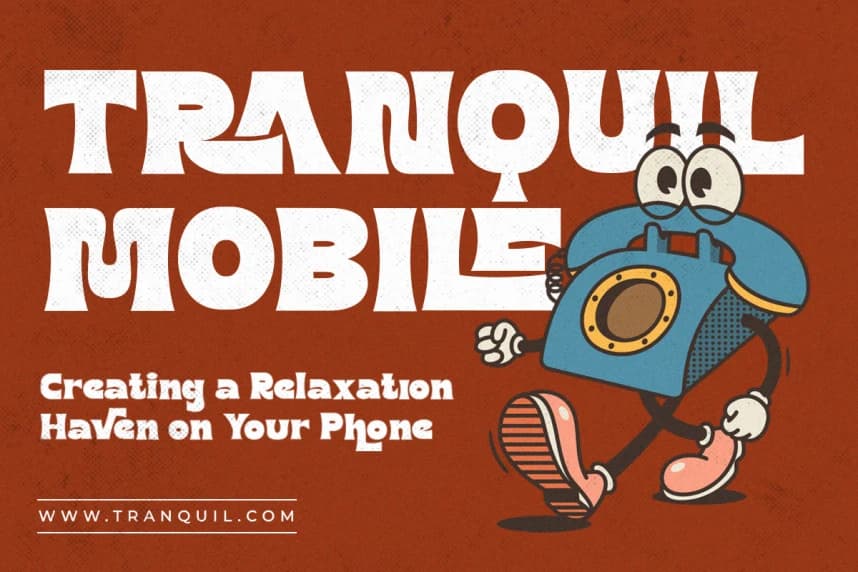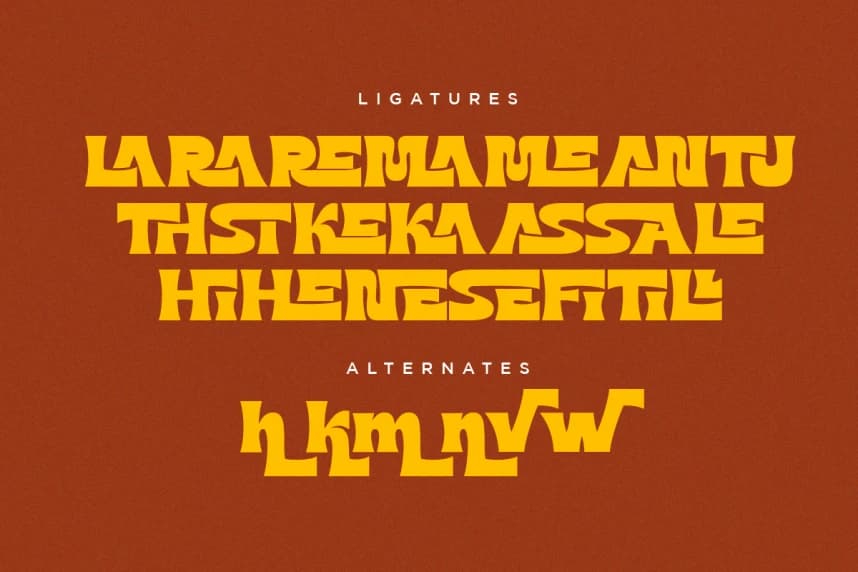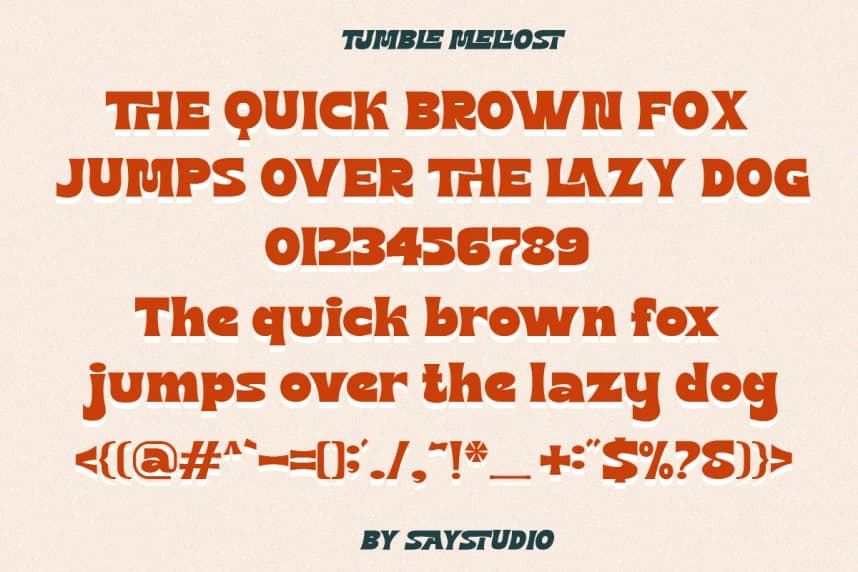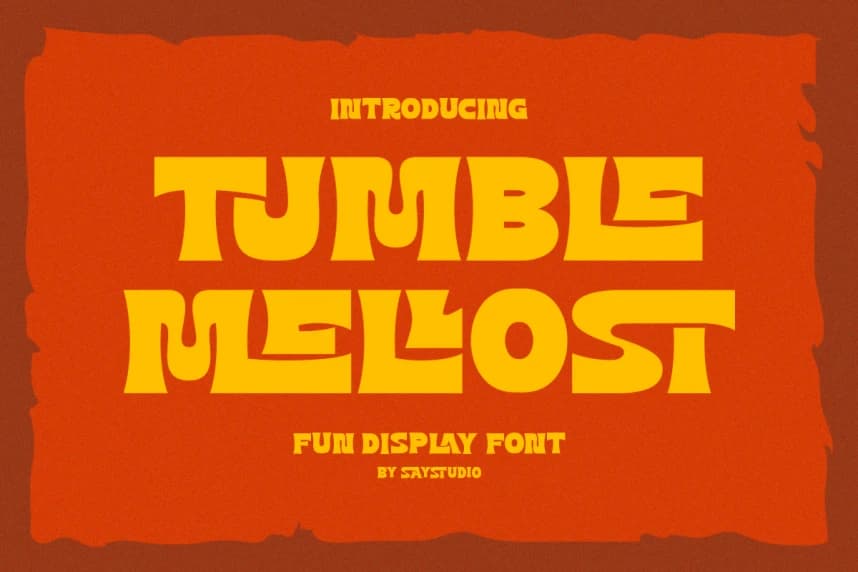
Tumble Mellost Font
Tumble Mellost Font, bizim yeni ve eğlenceli font koleksiyonumuz. Modern, eğlenceli ve resmi olanı bir araya getirir. Bu fontta pek çok alternatif ve ligatür bulunmaktadır; projelerinizde daha fazla eğlence için kullanabilirsiniz.
Tumble Mellost Font, yeni ve eğlenceli font koleksiyonumuz. Modern, eğlenceli ve resmi olanı bir arada sunuyor. Çok sayıda alternatif ve ligatür içerir; projelerinize daha fazla eğlence katmak için kullanabilirsiniz.